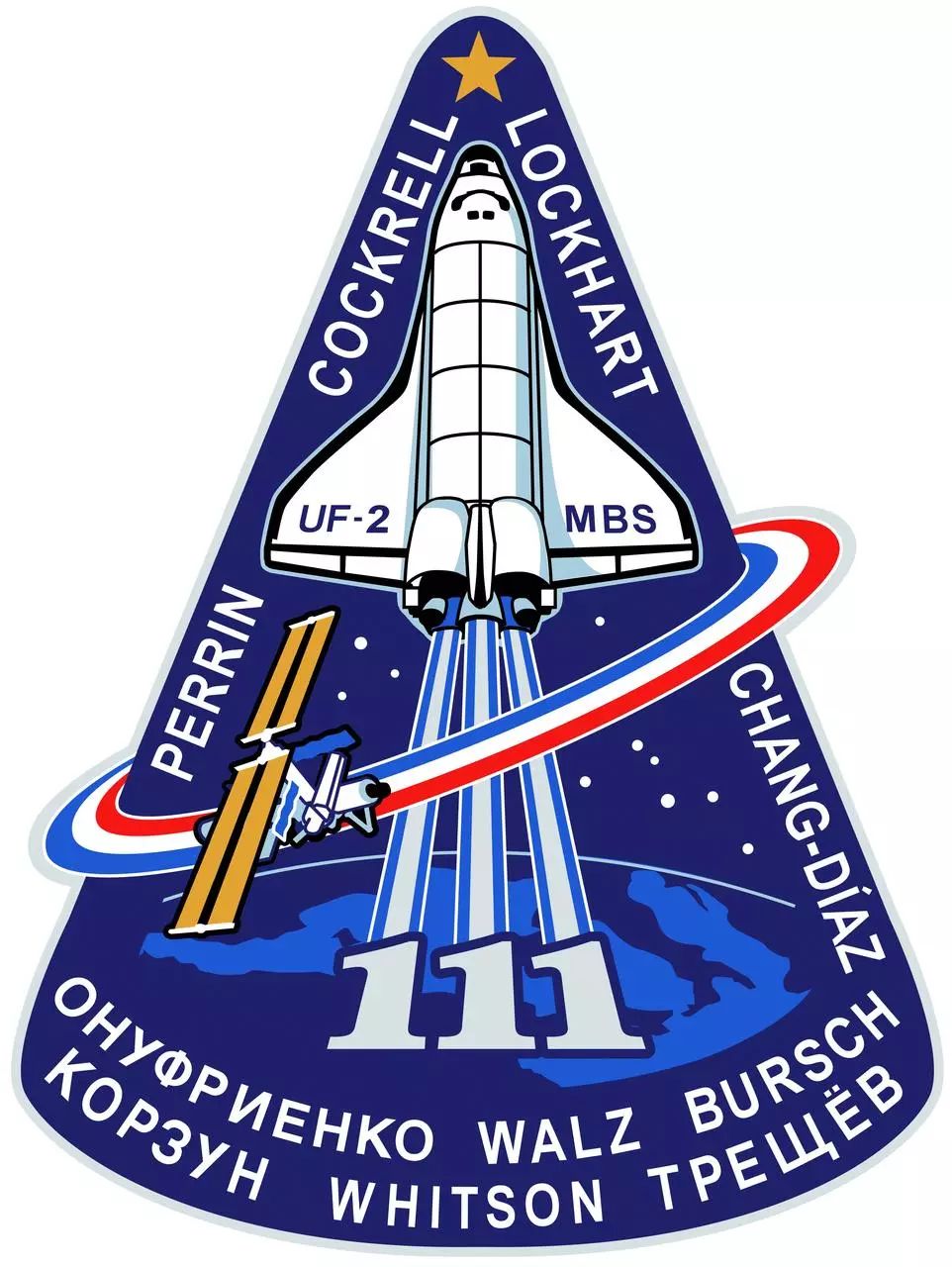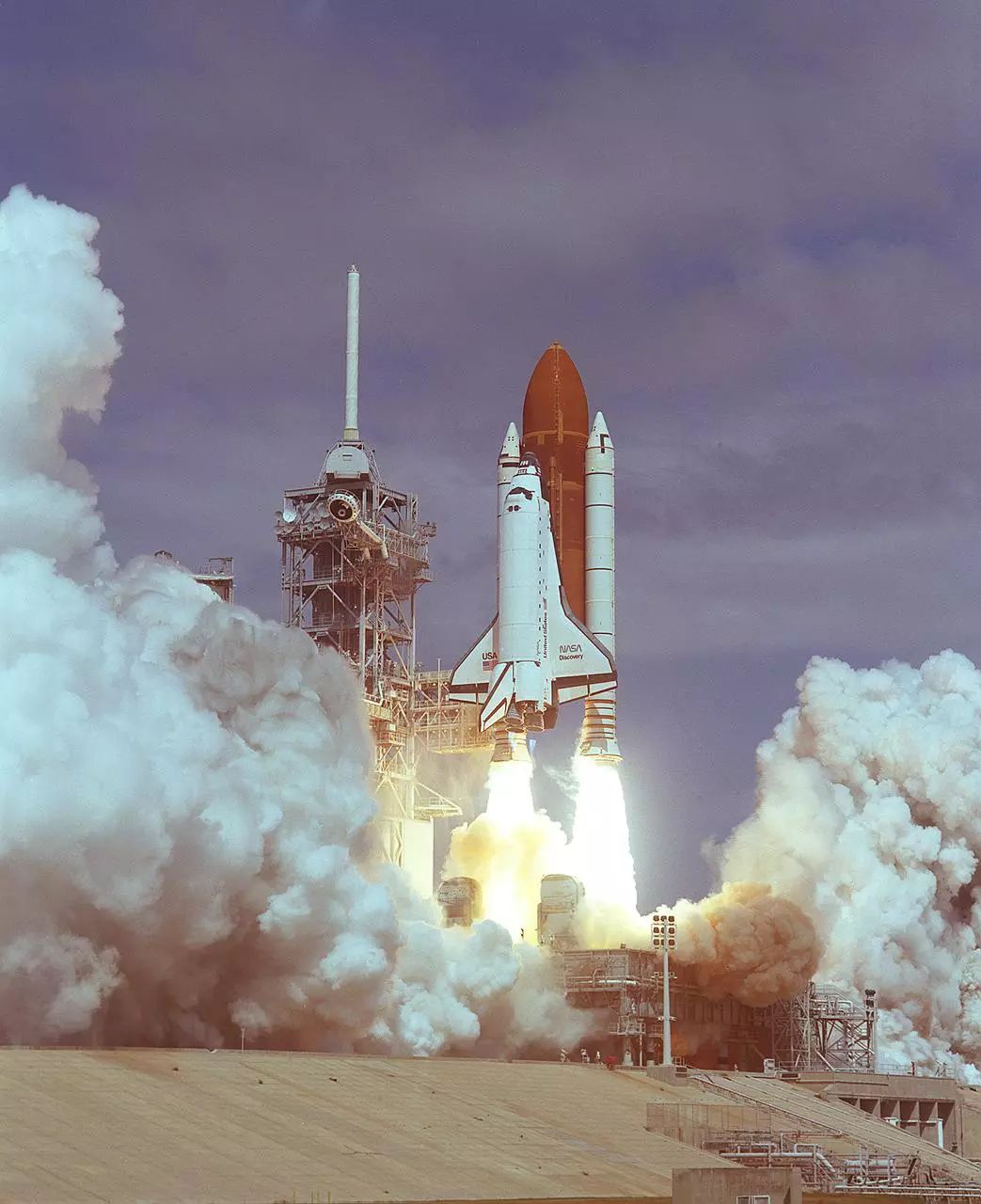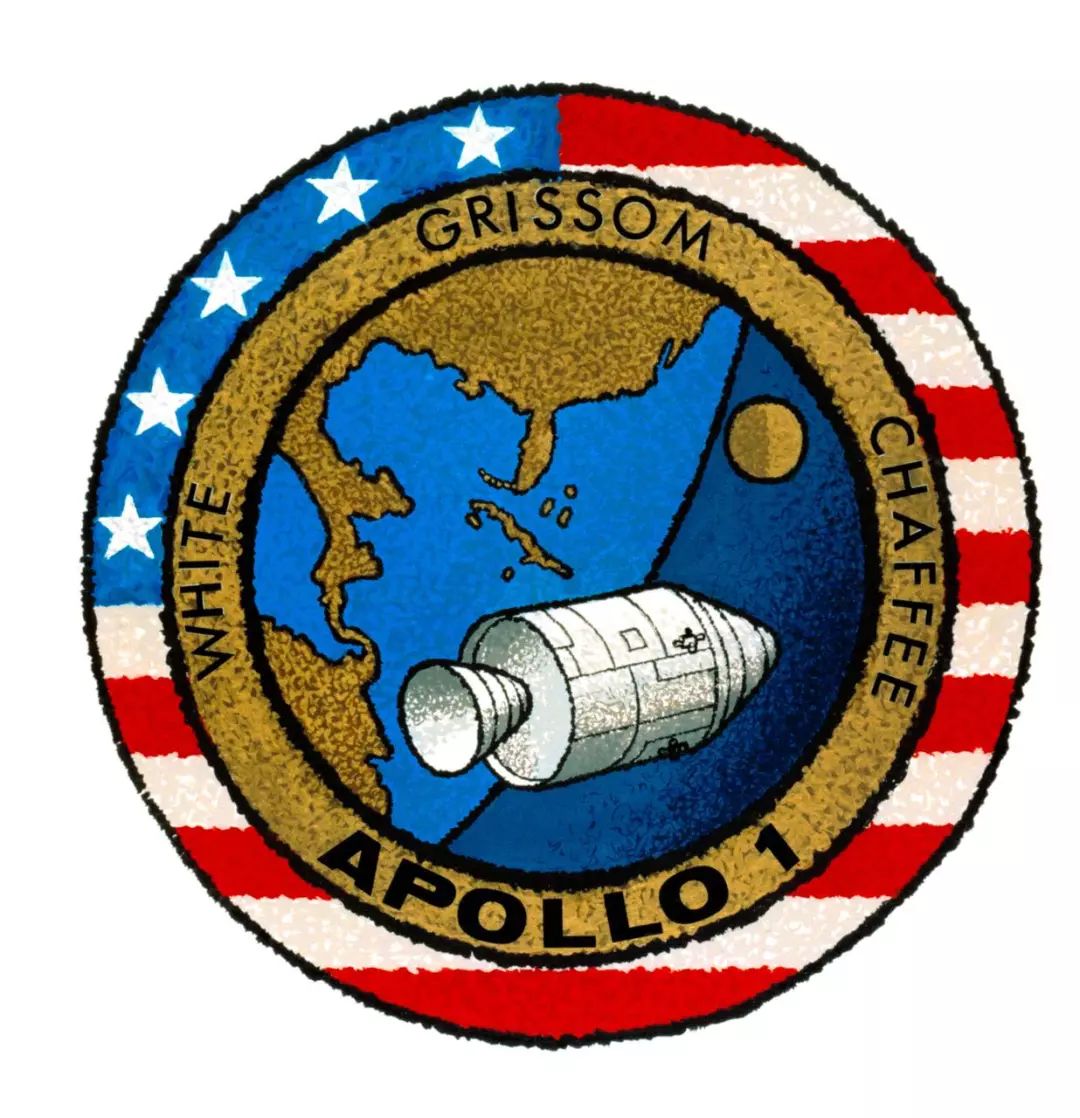
被航天事业“耽搁”的设计机构——NASA
提到NASA,可能大家想到的都是各种航天项目,卫星、航天飞机、火星车,但是NASA在各种项目的视觉设计上,也决不含糊。
首先当然是著名的“肉丸”标志,这也是普及率最高的一款,1959年由James Modarelli设计。
肯尼迪航天中心,工人们正在重绘logo。来源:NASA。
这个标志的蓝底代表星球,闪烁的星星代表太空,环绕的NASA的白色弧线代表太空旅行,红色的那个像箭头的图形代表的是用于进行风洞测试的超音速机翼模型。
红色箭头本尊。
1972年,美国国家艺术基金会发起了“联邦图形改进计划”,以提高美国政府机构的设计和传播的标准,NASA也在候选机构之列。
于是在1975年,由 Danne & Blackburn 设计的“蠕虫版” NASA 标志问世。
极具现代感的极简红色logo。来源:NASA。
他们还制作了视觉设计标准手册。
蠕虫标志使用标准手册。来源:NASA。
1983年,NASA的制服和宇航服上都是这个蠕虫标。来源:NASA。
1988年9月29日,发现号航天飞机发射升空。右侧机翼上可以看到当时NASA采用的蠕虫标志。来源:NASA。
不过这个标志很快就被弃用。
1992年,NASA再度启用“肉丸标”,一直沿用至今。
2001年7月21日,宇航员迈克尔·兰登·格恩哈特(Michael Landon Gernhardt)正在国际空间站进行舱外作业。背上清晰可见“肉丸标”。来源:NASA。
除了在自己的logo上下功夫,NASA的航天任务也都用心设计。
大名鼎鼎的阿波罗计划的徽标,从地球奔向月球。来源:维基百科。
阿波罗1号的徽标。来源:NASA。
阿波罗7号至17号的徽标。来源:NASA。
穿着宇航服的尼尔·阿姆斯特朗,胸前是NASA的肉丸标、他的名字以及阿波罗11号的任务徽标。1969年7月20日,他成为第一个登上月球的人类。来源:NASA。
航天飞机任务的徽标设计都非常出彩,看看下面几个...
1983年,挑战者号航天飞机升空,这是挑战者号第二次升空,也是史上第7次航天飞机任务。因此可以看到背景的夜空,七颗星星在闪耀,同时航天飞机的机械臂弯曲成“7”的形状;右侧黄色的星标代表此次任务成员,4名男性,1名女性。参与此次任务的女性航天员萨莉·莱德是第一位进入太空的美国女性。
1983年6月,挑战者号航天飞机升空,执行STS-7任务。来源:NASA。
2002年的这次任务由奋进号航天飞机执行,这个徽标的含义十分丰富,包括了参与这次任务的许多部门、国家等等。
航天飞机尾焰是宇航员办公室的标志;航天飞机机翼上的MBS,是此次要部署到空间站的来自加拿大的移动基座系统(Mobile Base System);国际空间站(ISS)绕行的轨道是红白蓝三色,代表参与这次任务的国家:美国、俄罗斯、法国和哥斯达黎加;底部的地球上显示的是意大利,因为意大利提供了一个多用途物流舱(Multi Purpose Logistics Module)。
背景中的10颗星表示此次参与任务的10名宇航员。徽标的上半部分一圈的名字,是执行航天飞机任务的4位宇航员的名字;下半部分的名字分别是这次离开空间站的3位宇航员和入驻空间站的3位宇航员。
2002年,奋进号航天飞机升空,执行STS-111任务。来源:NASA。
2002年,哥伦比亚号航天飞机对哈勃空间望远镜进行维护,以先进巡天照相机(ACS)替换了暗天体照相机(FOC),并且查看了冷却剂已经在1999年耗尽的近红外线照相机和多目标分光仪(NICMOS)。
徽标里,从哈勃的镜头中,可以看到遥远的深空。这次维修很快带来收获,2003年到2004年,先进巡天照相机和近红外线照相机和多目标分光仪共同完成了哈勃超深空视场。
2002年3月,哥伦比亚号航天飞机执行STS-109任务,对哈伯空间望远镜进行维护。来源:NASA。
哈勃超深空视场,是天炉座的一小部分,它是截至2006年为止以可见光拍摄的最深远的宇宙影象,显示的是超过130亿年前的情况。来源:维基百科。
还有下面这些…
1997年8月,发现号航天飞机执行的STS-85任务徽标。来源:NASA。
哥伦比亚号在1983年执行STS-9任务时的徽标,背景中的9颗星以及航天飞机的轨迹组成的9,表示这是第9次航天飞机任务。来源:NASA。
2001年,亚特兰蒂斯号航天飞机执行STS-98任务,这是国际空间站组装阶段的一个里程碑事件,美国的“命运”号实验舱来到太空。来源:NASA。
2009年,NASA宇航员弗雷德里克·W·斯特科在国际空间站与之前的任务徽标合影。来源:NASA。
除了这些载人航天任务,其他的徽标设计也都毫不马虎。
火星科学实验室,这个计划下辖的探测器在2011年11月26日发射,2012年到达火星。是的,就是那个著名的好奇号火星车。来源:NASA。
刚到达火星不久的洞察号的徽标,它的任务是探测火星内部,徽标很形象。来源:NASA。
战神I-X火箭logo。来源:NASA。
费米伽玛射线空间望远镜的logo。来源:NASA。
还有一些比较特别的:
NASA 60周年纪念logo。来源:NASA。
官方解释的太多了,挑几个细节说吧。logo下半部分的地球,正好转动到美国,表示NASA的支撑来源;两个飞行器的轨迹也组成了一个数字“6”,代表6 decades。
除了60周年,最近还是阿波罗计划50周年,NASA也有特别制作的logo。
阿波罗计划50周年纪念logo。来源:NASA。
贯穿“APOLLO”的是地球的弧线,纪念第一次从月球看到地球的瞬间;字母O里面分别是月球和火星,代表回到月球和“next giant leap”是去火星。
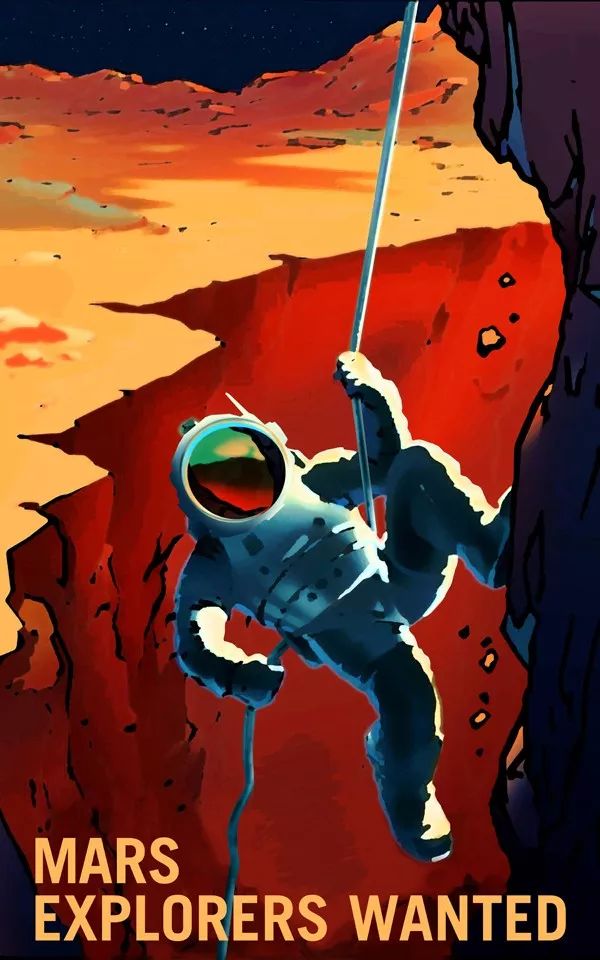
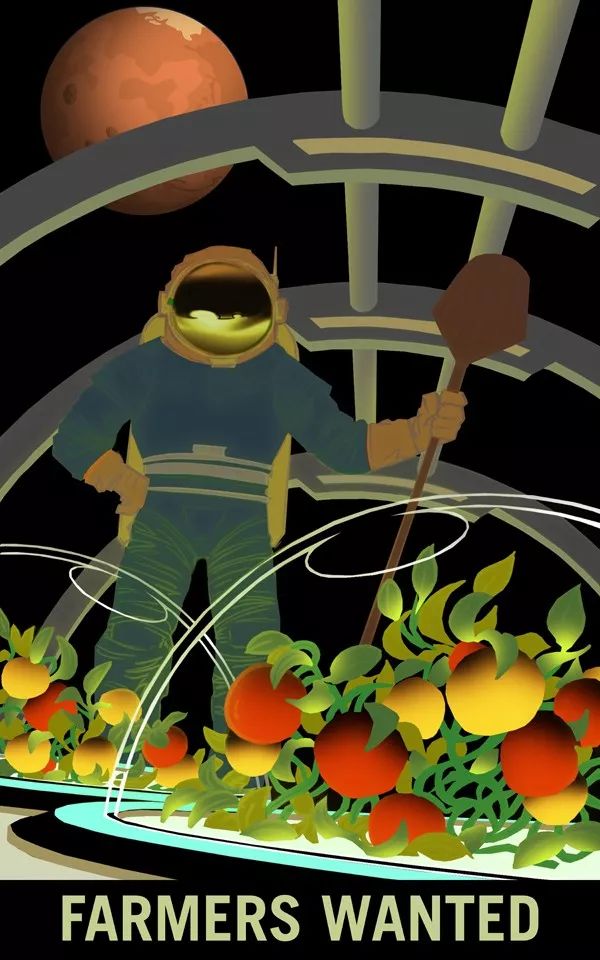
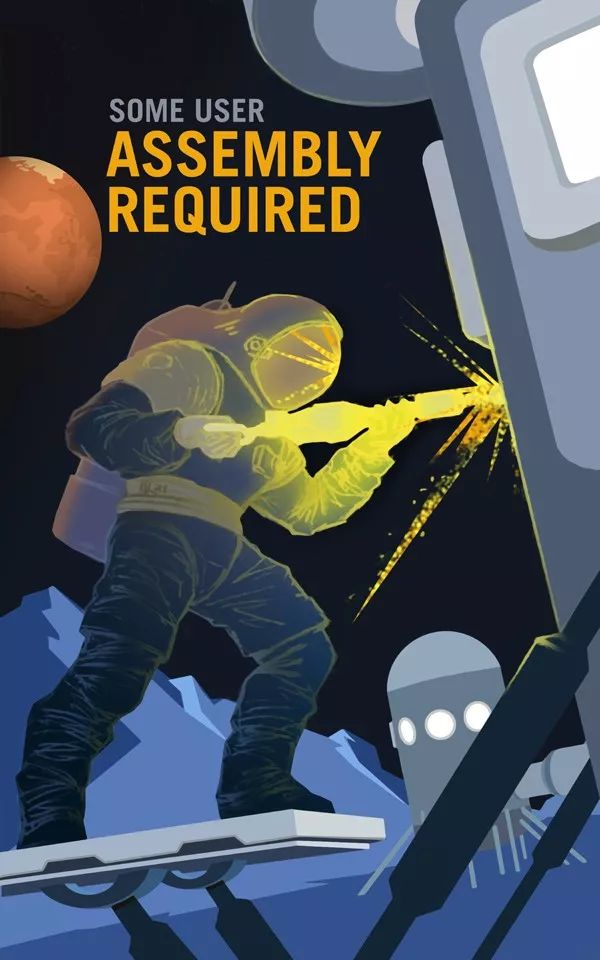
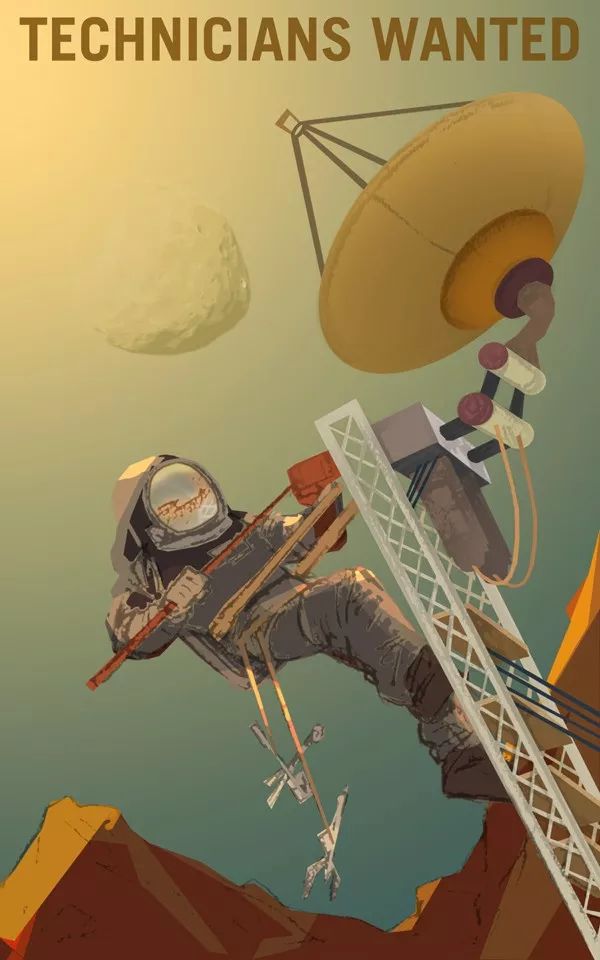
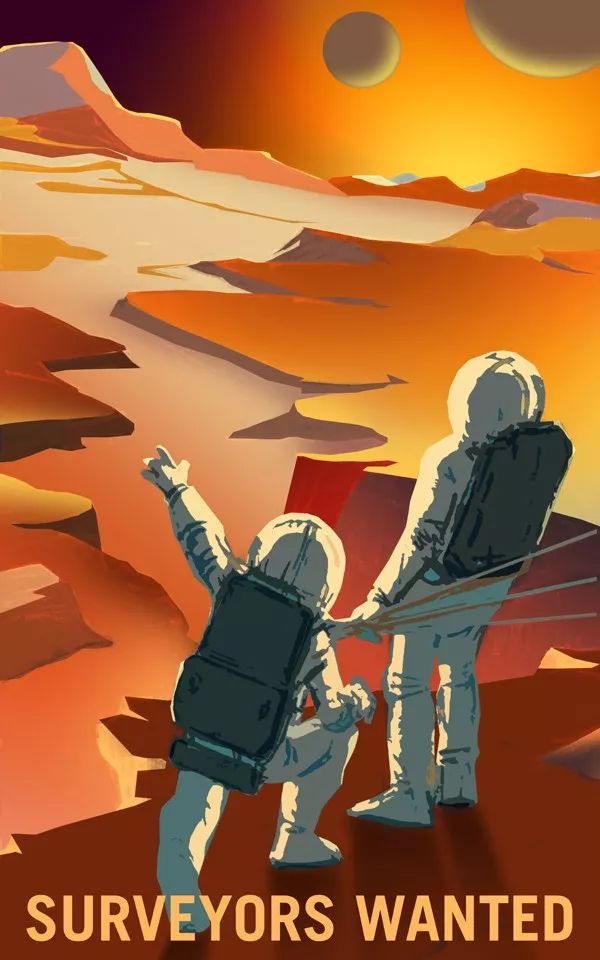
上面是NASA 2009年在肯尼迪航天中心做的一次展览的海报。来源:NASA。
这是NASA JPL的视觉创意团队The Studio制作的“Visions of the Future”系列海报中的一张。来源:NASA。
NASA的设计,都兼顾美与科学。就拿Visions of the Future来说,都是根据对星球的探测做出的未来畅想,每一张海报,都吸纳了来自JPL科学家的意见。
创世之柱。图像团队根据不同元素的不同颜色进行渲染合成,最后再调整一下立体效果。来源:TED.com